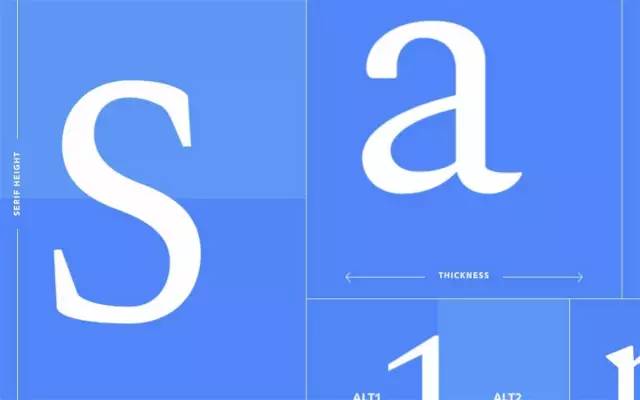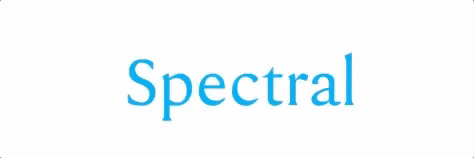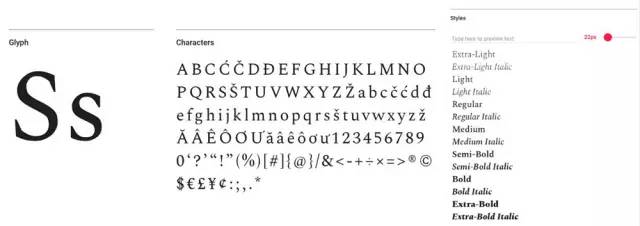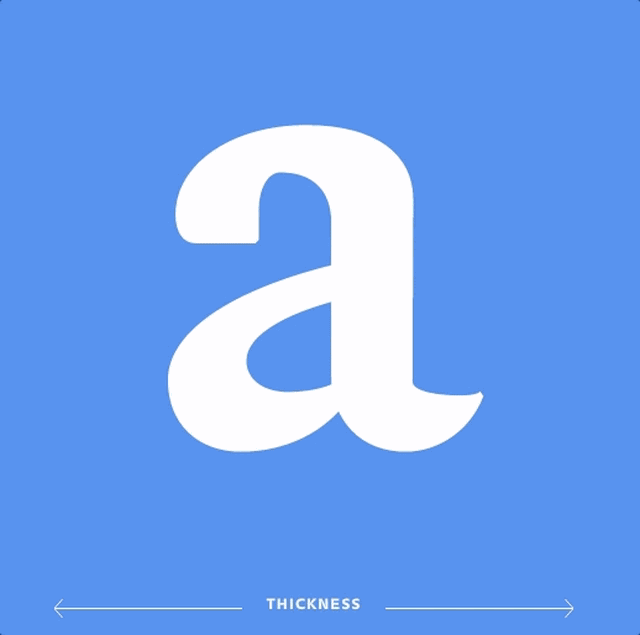
Spectral 字体,可供设计师或字体爱好者随意调整字体形态
两个月前,Google 和 Adobe 联手推出的思源宋体赢得呼声一片。才没过多久,Google 在字体方面又有新动作,推出了自己的首款“参数化”字体 Spectral,可供设计师或字体爱好者随意调整字体形态,进行个性化设计。
但如果准确地说,Spectral 应该是 Google 第一款被转化为“参数化”的字体。这款字体原由 Google 和法国字体设计公司 Production Type 合作,专门为流畅的电子阅读体验而设计的一款免费字体,旨在减少阅读过程中可能由字体产生的干扰,尤其合适用于网络长文。而且,即使在不同的电子媒体和设备上,也会根据载体特点进行自动适配。
随后,这款字体被基于参数的字体生成器 Prototypo 转化为参数化字体,并可在 Prototypo 平台上基于 Spectral 字体进行“傻瓜式”设计。Prototypo 还用 Spectral 衍生出来的十种字体做了个魔性的展示页面,让大家在试玩前感受了一把用参数调整字体是多么方便。
设计界面最左边是各种可调节的字体参数:x 字高、衬线弧度、字间距、降部、升部、大写字高……
看不懂?没事,因为操作界面的中间和最右边都是“即改即有”的实时预览,而且用户还能在最右边输入自己想测试效果的内容。
其实,微软去年就联手 Adobe、苹果和 Google 合作开发 OpenType 字体。OpenType 可变字体将同一字体的所有信息压缩为一个文件,使得文件体积大为缩小,减少了对网页带宽的占用,而且还能对字体进行细微调节。而这次的 Spectral 应该是 Google 对可变字体尝试的一小步。